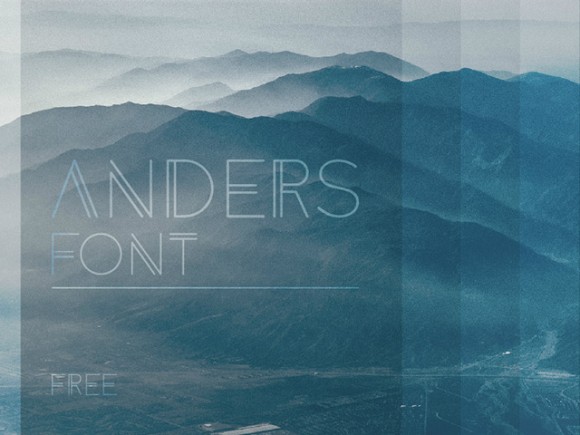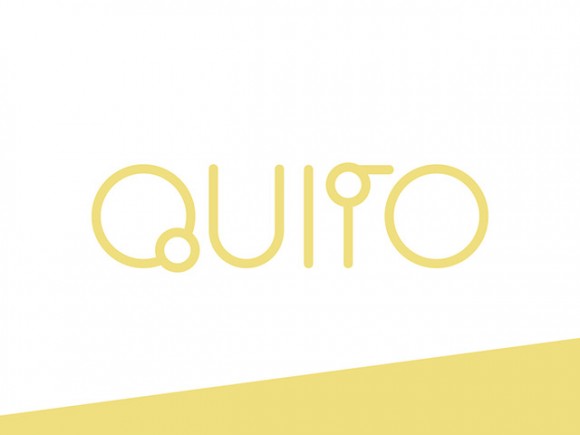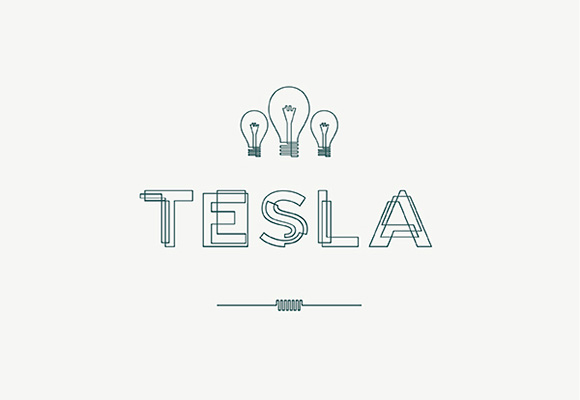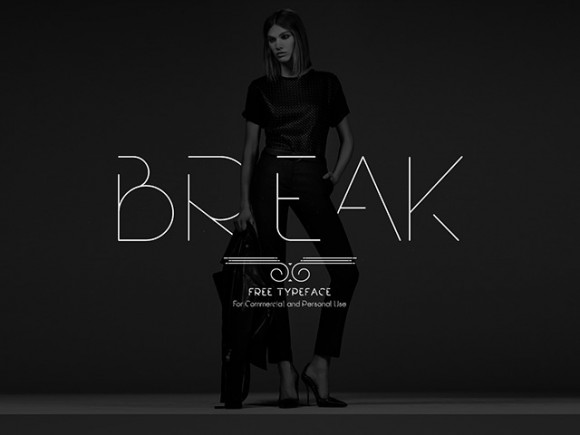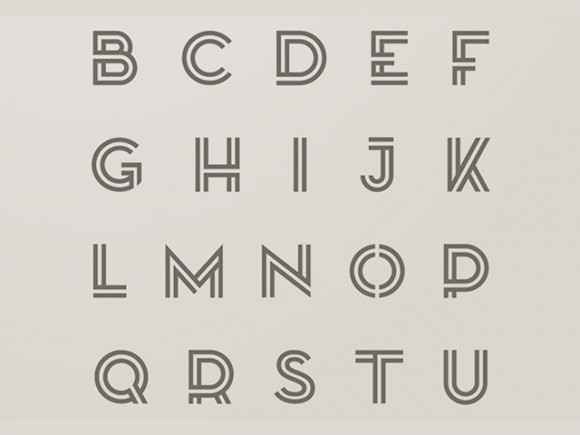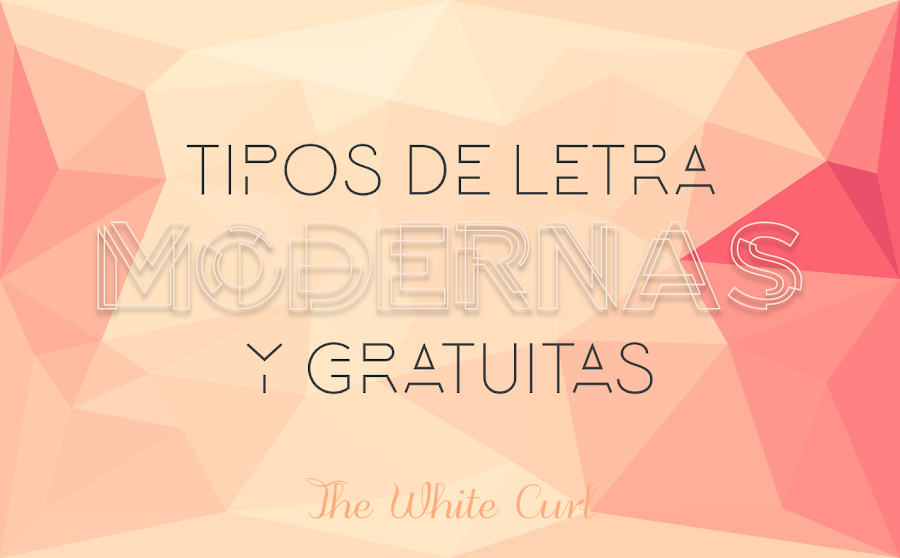
Tipografías Modernas. Descarga Gratis.
Las que me han seguido desde hace algún tiempo ya sabrán que me encantan las tipografías y últimamente estoy obsesionada con éstas tipografías muy geométricas y modernas, me parecen muy lindas y quería compartirlas con ustedes, así que para el post de hoy les presento una selección de tipografías modernas y geométricas .